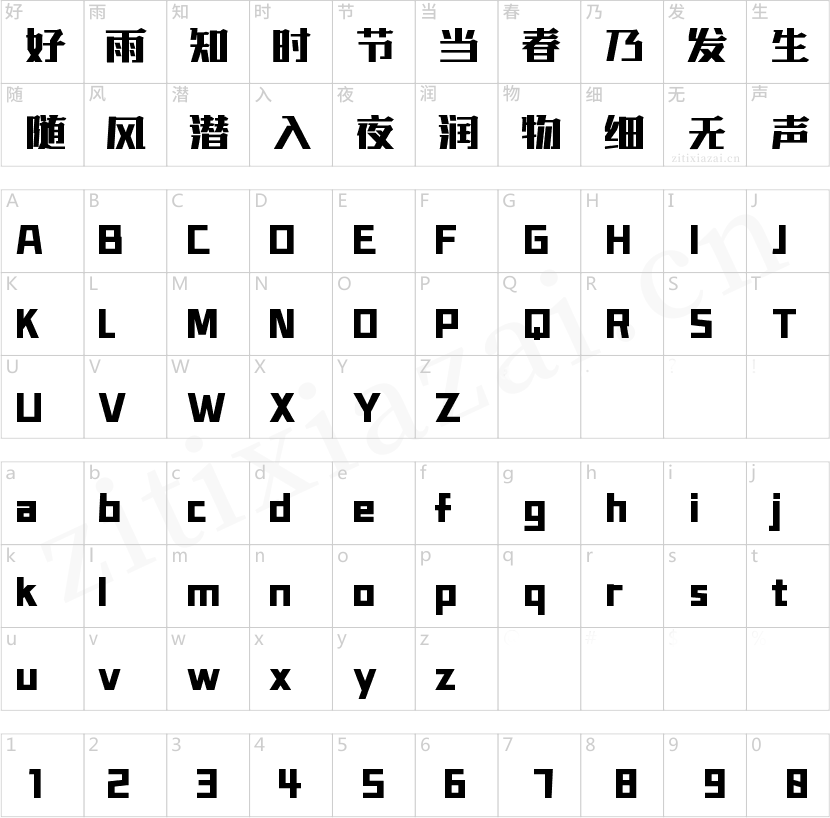
字魂方块黑
字魂方块黑,这款字体结构工整、笔画清晰,兼顾美观与易读性,适用于标题、正文、海报、包装、LOGO 等多种场景。字形优雅稳定,风格百搭耐看,适配日常排版与创意设计,让文字呈现更舒适、更具质感。字魂方块黑一笔一画,皆是细节,以均衡的比例、流畅的线条打造舒适视觉体验,字形端正大气,风格简约现代。无论是商业设计、品牌宣传还是日常排版,都能轻松驾驭,让文字更有格调与力量。字魂方块黑字体下载。
字魂字体字小魂方块黑字体是由字魂创意字库设计并生产的一款可商用的字体,被收录于字小魂系列。该字体支持GB-2312标准以及最新的字魂ZH7144标准,包含7144个中文、字母、符号和数字,字体类型偏向黑体,具有简约的风格,在市面上广泛用于成人用品、视频影视、标题字等场景。